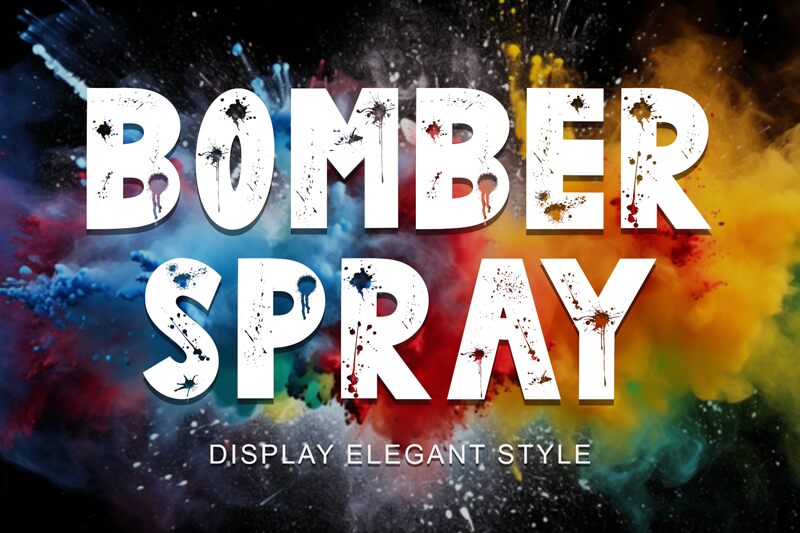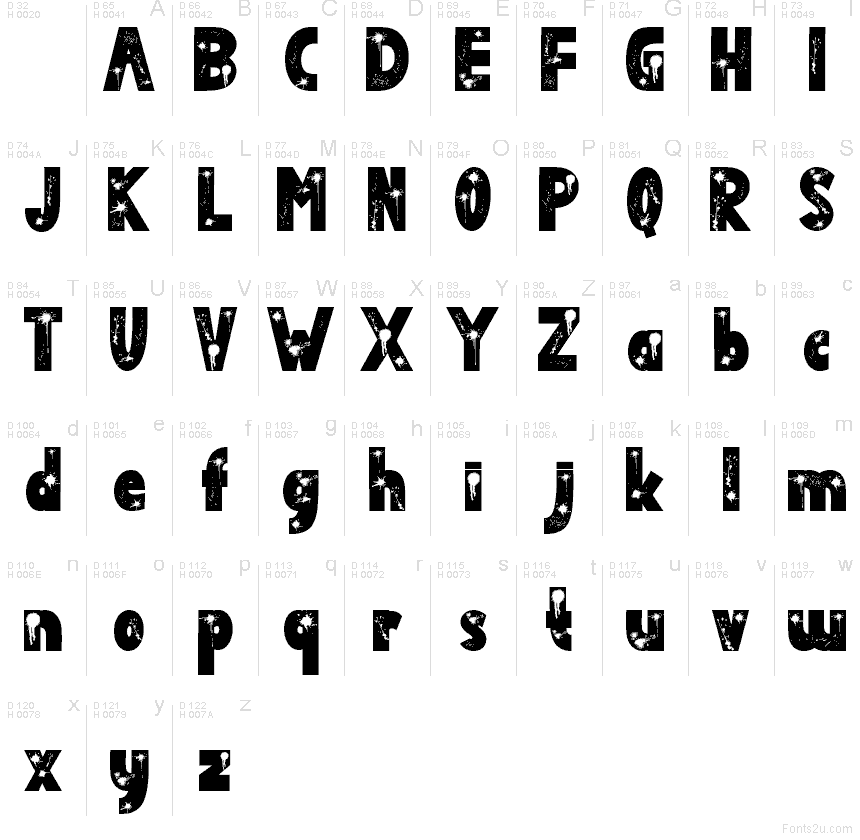
Bomber Spray
Bomber Spray de Yoga Letter est une police d'affichage décorative gratuite qui se distingue par son aspect graffiti, avec des éclaboussures de peinture et des gouttes qui coulent sur ses formes arrondies. Les lettres conservent une structure compacte et fluide sous les effets de peinture brute, donnant à ce design l'aspect d'un lettrage tagué plutôt que d'un pochoir rigide.
Bomber Spray est parfaite pour les titres d'affiches, les visuels street-art, les flyers d'événements, les pochettes d'albums et les réseaux sociaux où une finition à la bombe est nécessaire. Cette police gratuite est idéale pour les autocollants, les packagings et les illustrations qui demandent un rendu peint plutôt qu'une impression classique.